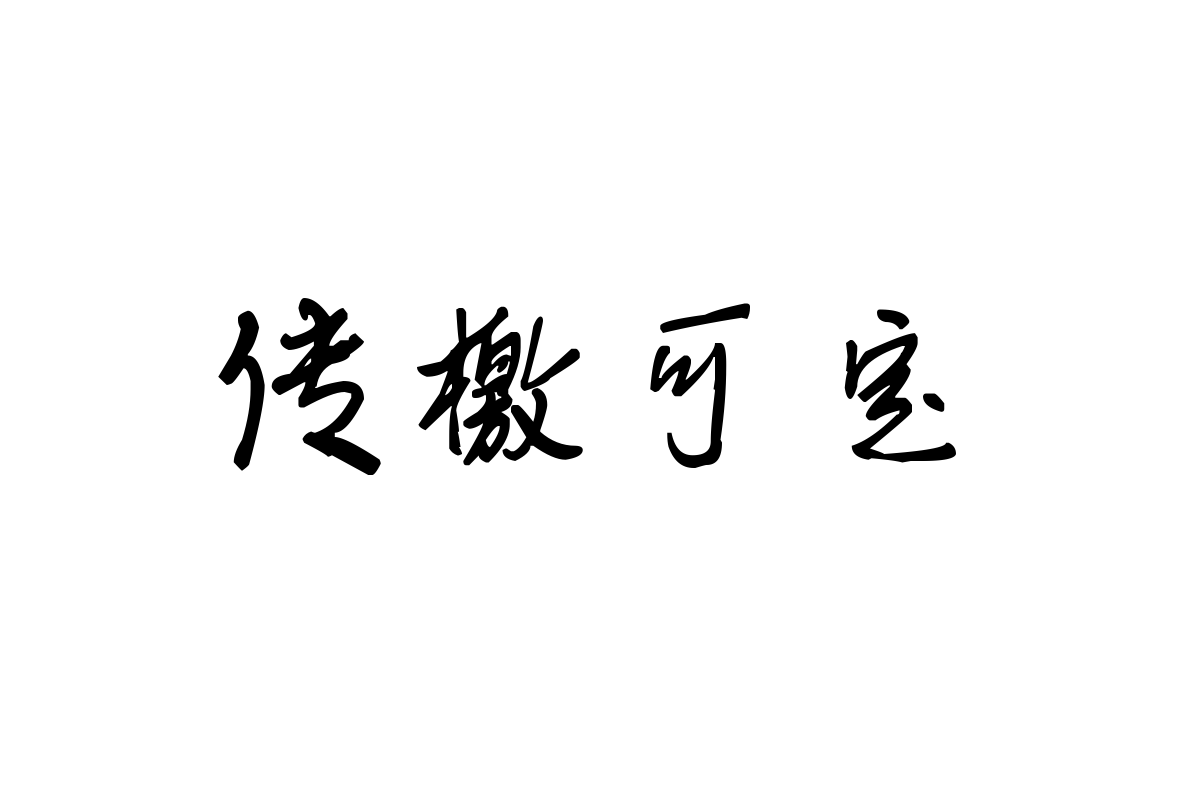
汉呈清风行是一款具有独特书法风格的字体,其特点是笔画流畅、结构紧凑、风格清新自然。这款字体适用于需要展示传统文化和艺术气息的场合,如书籍、报刊、广告等。
汉呈清风行字体的特点如下:
1. 笔画流畅:汉呈清风行的笔画线条流畅,给人一种优雅的感觉。这种流畅的线条使得字体更加美观,适合用于需要展示文字美感的场合。
2. 结构紧凑:汉呈清风行的字形结构紧凑,每个字的笔画都紧密相连,没有多余的空间。这种紧凑的结构使得字体显得更加简洁、大方,适合用于需要突出主题的场合。
3. 风格清新自然:汉呈清风行的字体风格清新自然,给人一种宁静、舒适的感觉。这种清新自然的设计风格使得字体更加适合用于需要展示轻松、愉快的氛围的场合。
4. 适用范围广泛:汉呈清风行字体适用于各种场合,无论是用于书籍、报刊、广告还是其他印刷品,都能展现出其独特的魅力。
总之,汉呈清风行是一款具有独特书法风格的字体,其笔画流畅、结构紧凑、风格清新自然的设计风格使得它在各种场合都能展现出独特的魅力。